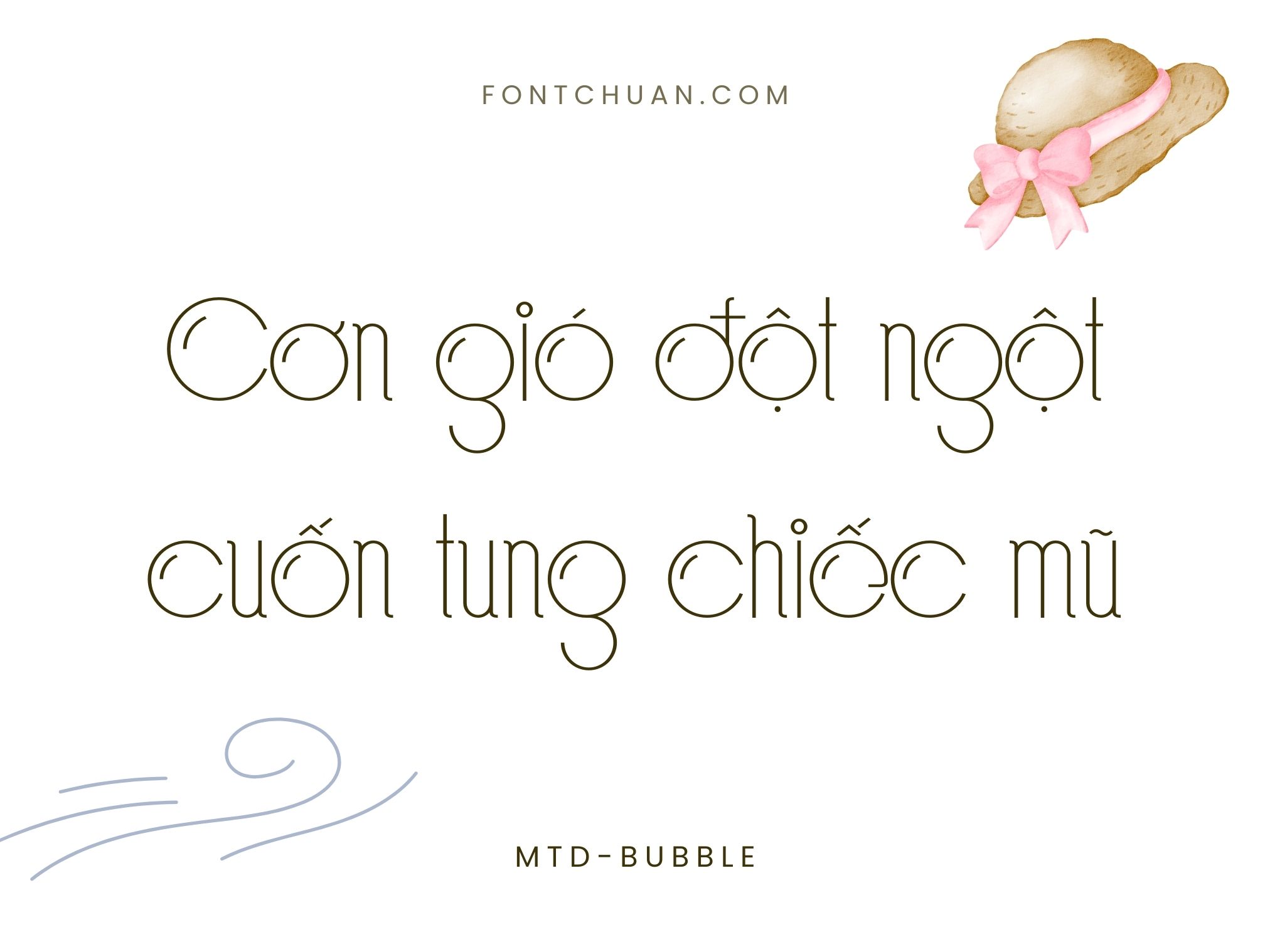
Font MTD Bubble là một kiểu chữ trang trí vui nhộn, được thiết kế với phong cách chữ bong bóng độc đáo. Font này hỗ trợ đầy đủ tiếng Việt cùng hơn 90 ngôn ngữ khác, mở rộng khả năng ứng dụng trong các thiết kế đa ngôn ngữ. Đây là một trong những phông chữ được cộng đồng thiết kế đánh giá cao và sử dụng trong nhiều dự án sáng tạo, đáp ứng nhu cầu đa dạng của người dùng.
MTD Bubble nổi bật với các đường nét mềm mại và hình dáng bong bóng thú vị, tạo cảm giác thân thiện và vui tươi. Font rất phù hợp cho các thiết kế liên quan đến trẻ em, giáo dục, thiệp mời, bao bì sản phẩm và các ấn phẩm đòi hỏi sự sáng tạo và độc đáo. Các ngành nghề phù hợp bao gồm quảng cáo, giáo dục, công nghệ, thiệp cưới và ảnh cưới. Font này cũng lý tưởng cho các sự kiện như Tết, Giáng sinh, Valentine và các lễ hội khác.